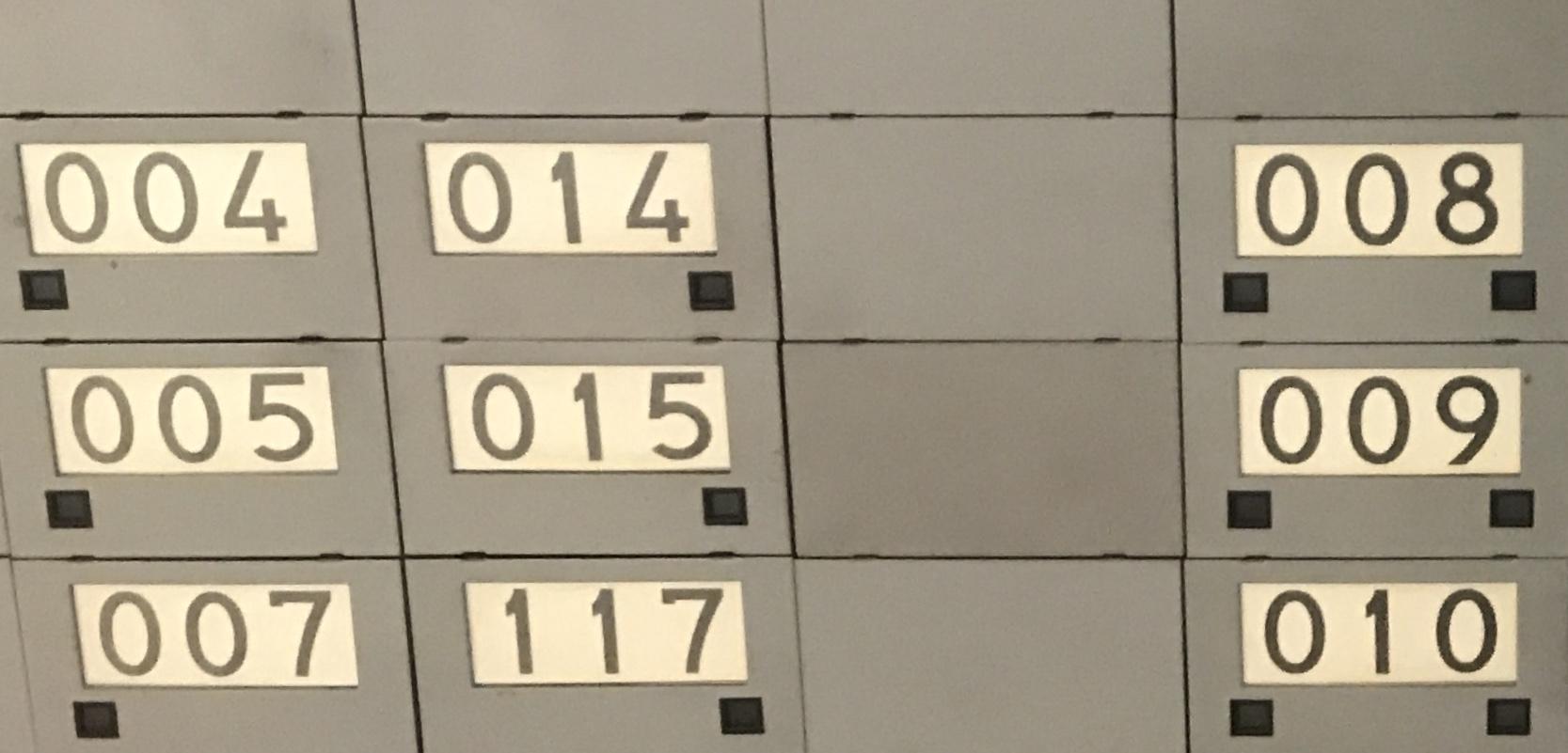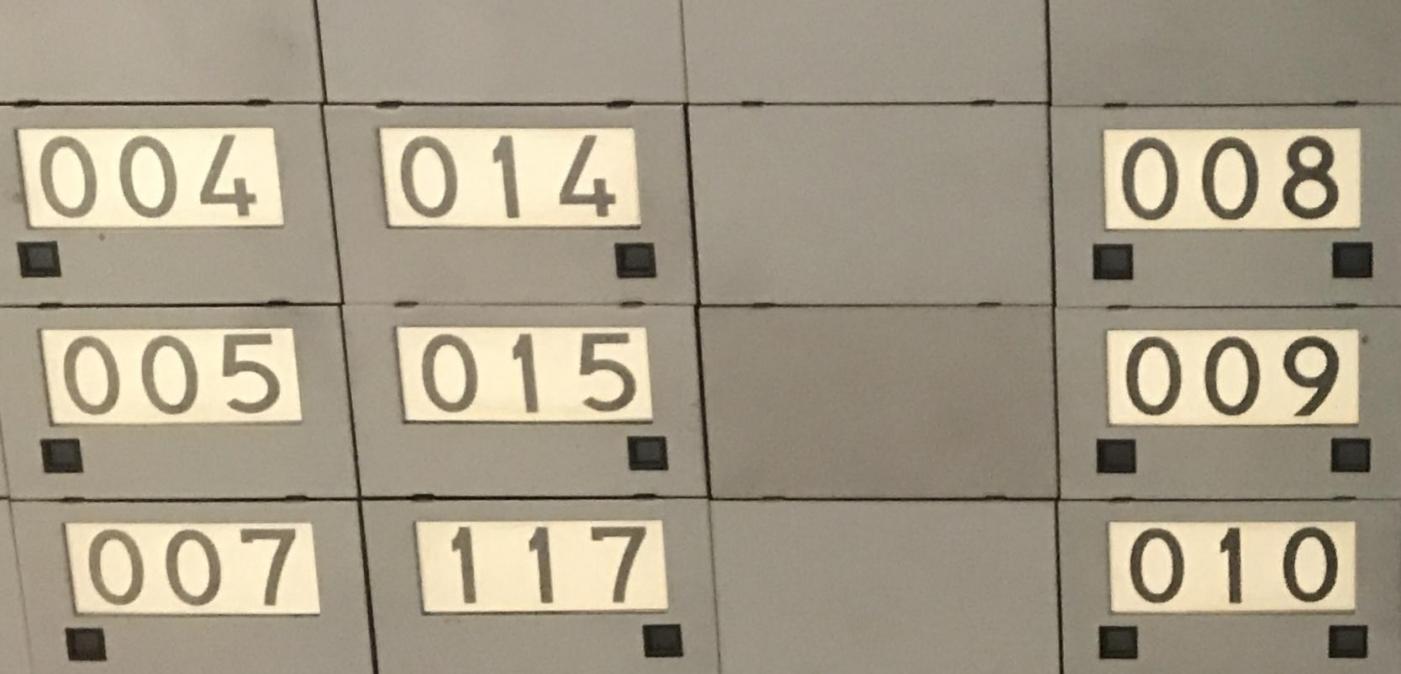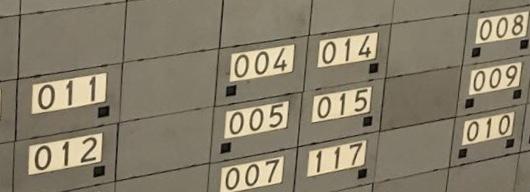
Suche Schrift zur Bezeichnung von Eisenbahn-Stellwerken der Fa. Siemens
Ich suche folgende Schriftart - ein Beispielbild ist angehängt.
Verwendet  wurde diese Schriftart ab etwa 1960 (vermutlich, ab etwa 1970 definitiv!) von der Firma Siemens, um Bezeichnungsfelder auf Stellwerksanlagen der Eisenbahn dazustellen. Der Bediener sah so auch von etwas Entfernung, wie Gleise und Signale heißen.
Damals wurden normalerweise für derartige Beschriftungen keine Satzschriften verwendet, daher wird es zu genau dieser wahrscheinlich keine Schrift-Entsprechung geben. Die "DIN Breitschrift" könnte Pate gestanden haben, gleichwohl sehen mir die Zahlen aus, als hätte man bei der Gestaltung Wert auf größtmögliche Unterscheidbarkeit gelegt.
eine weitere Möglichkeit wäre, Siemens anzuschreiben. Die haben sicher, wie jeder größere Konzern auch ein Archiv.
Gut möglich dass man dort auch stöbern darf. Was natürlich auch nicht schlecht wäre, wenn man die Schrifttafeln kopieren,fotografieren und/oder scannen darf. Man kann ja Siemens anbieten, dass die fertige Schrift wieder an Siemens zurück geht. Quasi als Gegenleistung unentgeltlich.